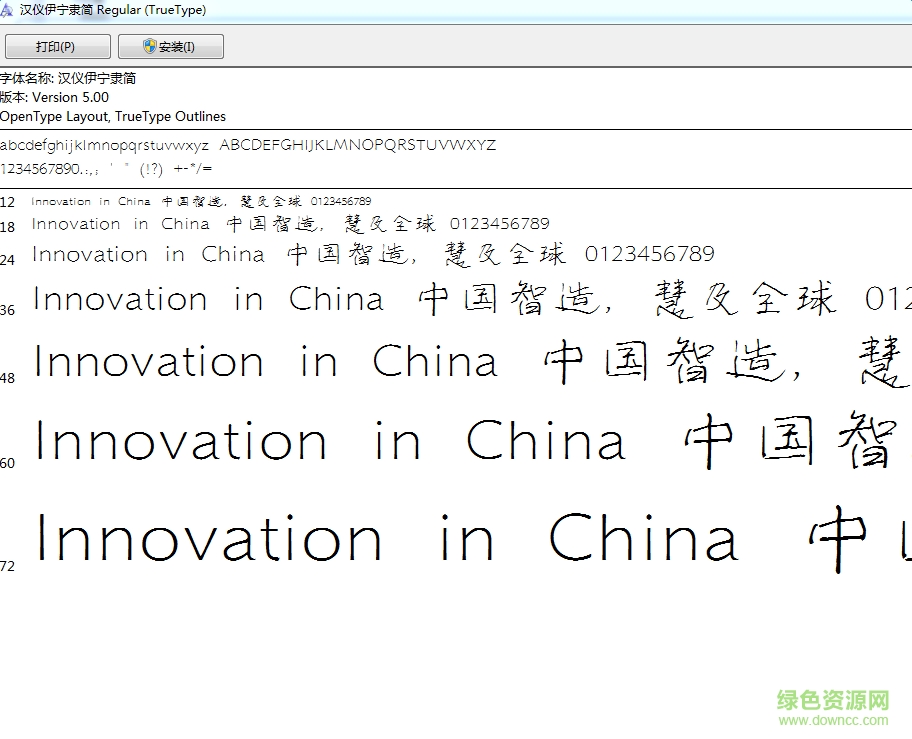
漢儀伊寧隸簡是一款漢儀類清新簡約風(fēng)格字體軟件,伊寧隸簡體以行書的優(yōu)美搭配隸書的文雅,整體效果以現(xiàn)代簡體展現(xiàn)出來,非常的好看,還有更多好看的字體歡迎來綠色資源網(wǎng)下載使用!
漢儀伊寧隸簡是行書與隸書的融合體,特征為:樸拙、流暢、隨意、雅致而又不失講究,書寫講究特征,具有行書的流暢、瀟灑、隨意與隸書的雅致,適用于廣告設(shè)計、平面設(shè)計、印刷包裝、藝術(shù)設(shè)計、網(wǎng)站設(shè)計領(lǐng)域。
此字體筆畫細膩行如流水,與時尚簡體字搭配,現(xiàn)代氣息十足,整體效果比較非主流,用來裝逼再合適不過了!